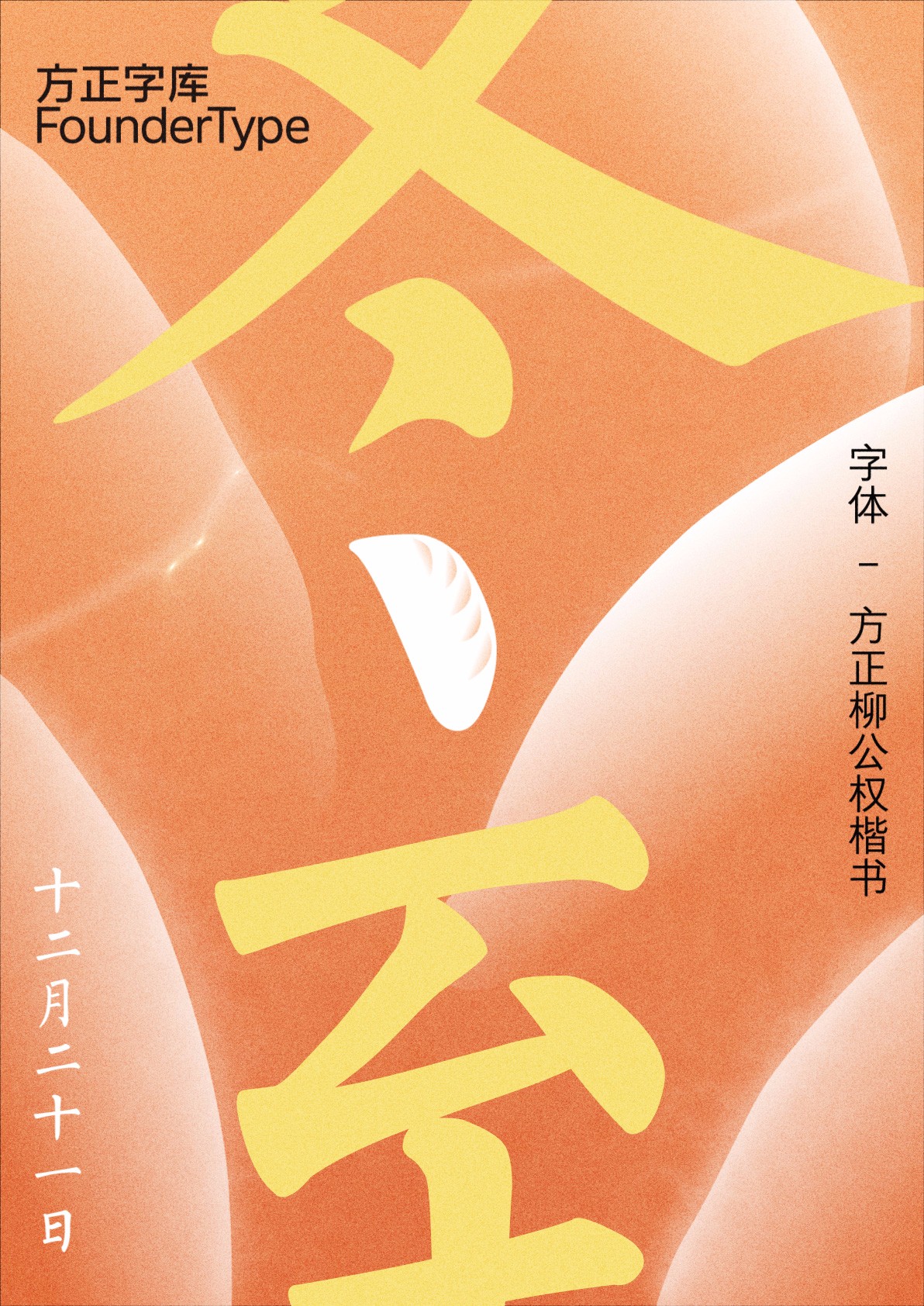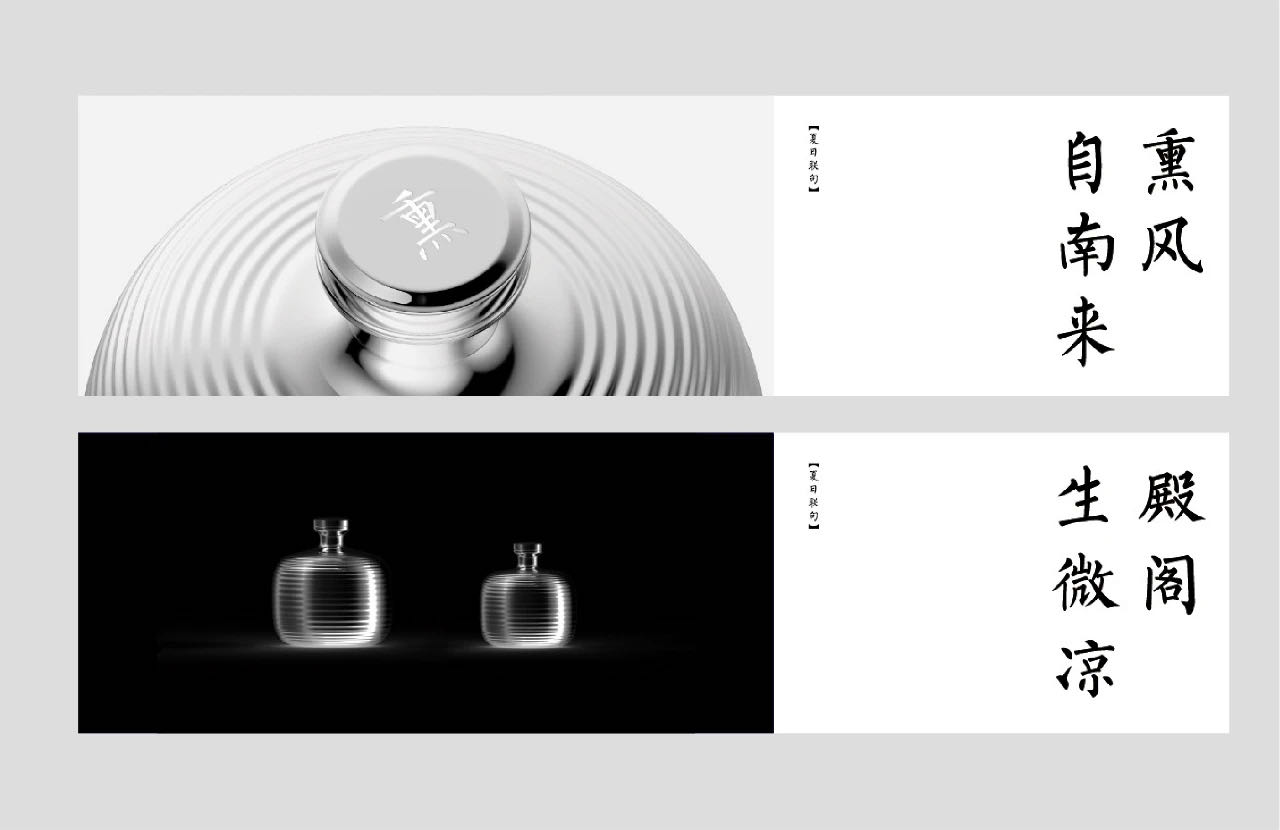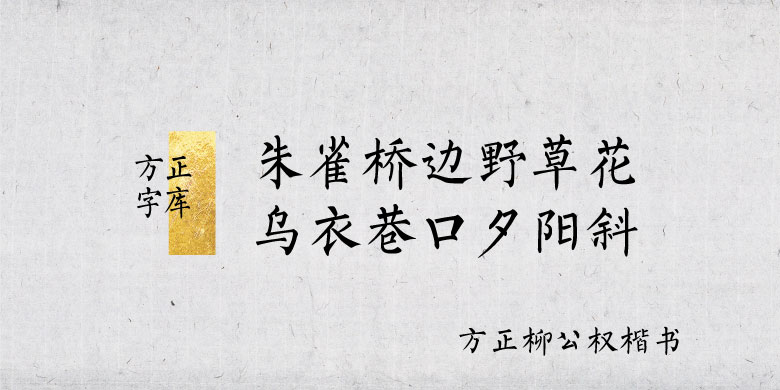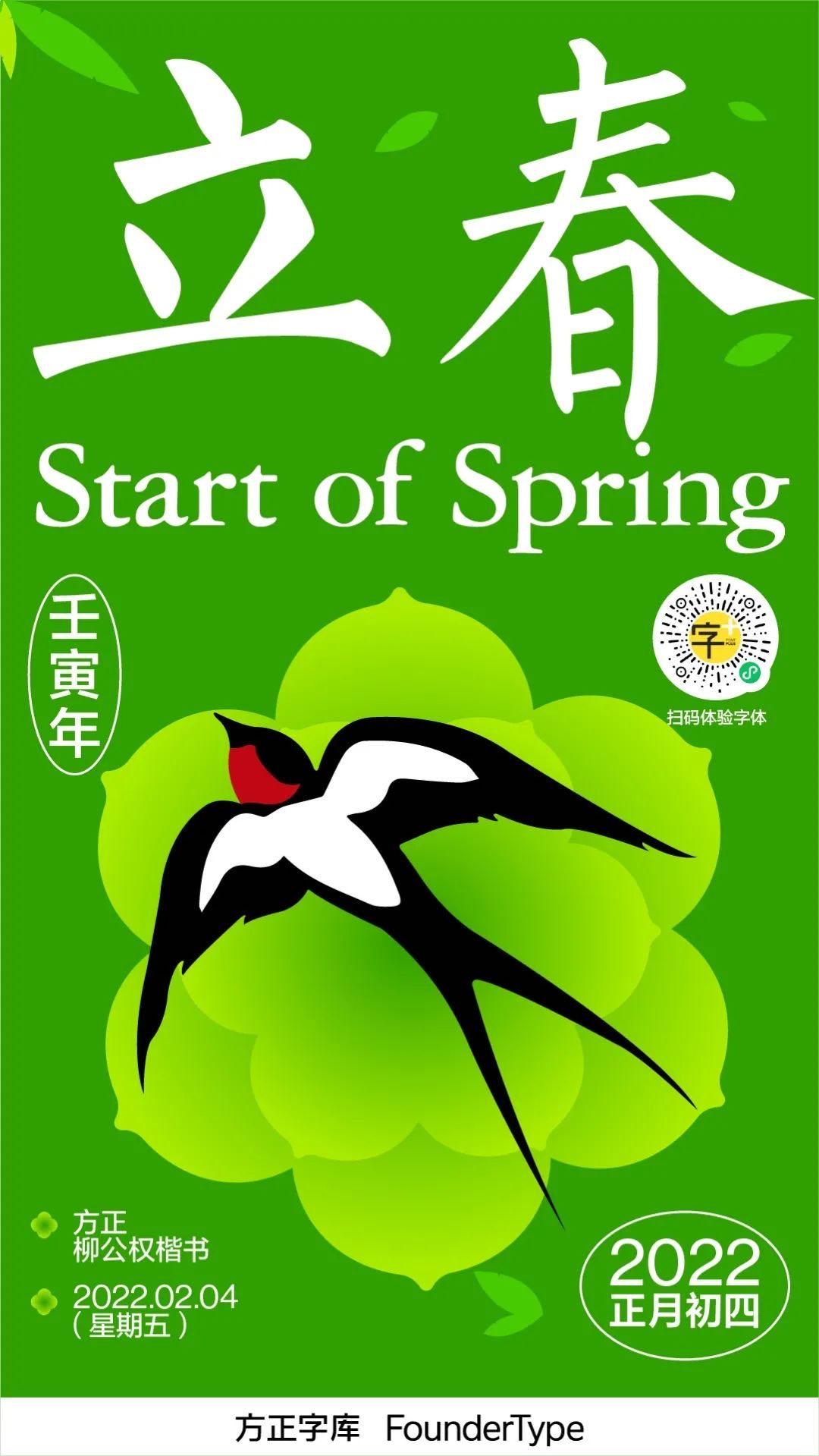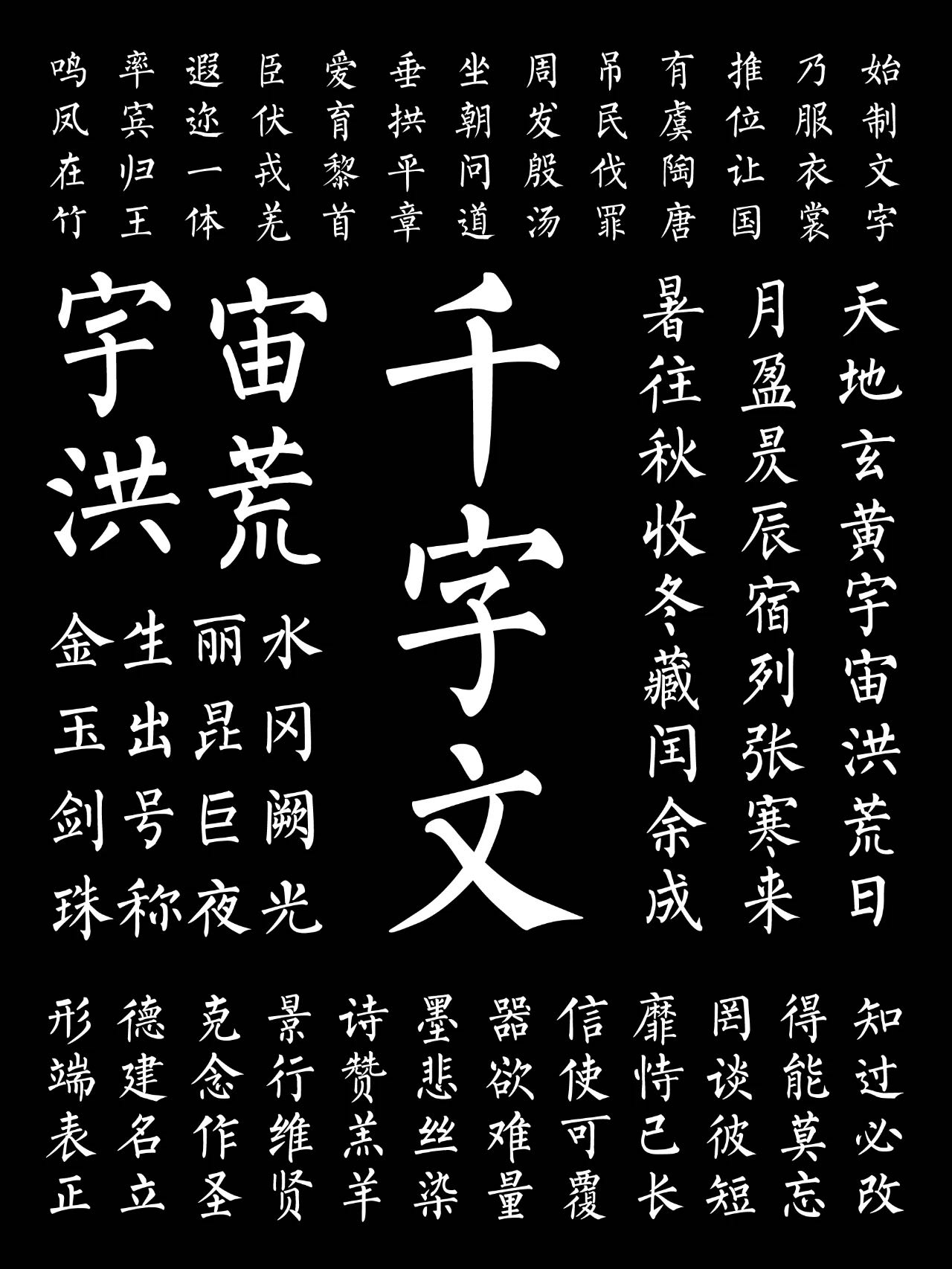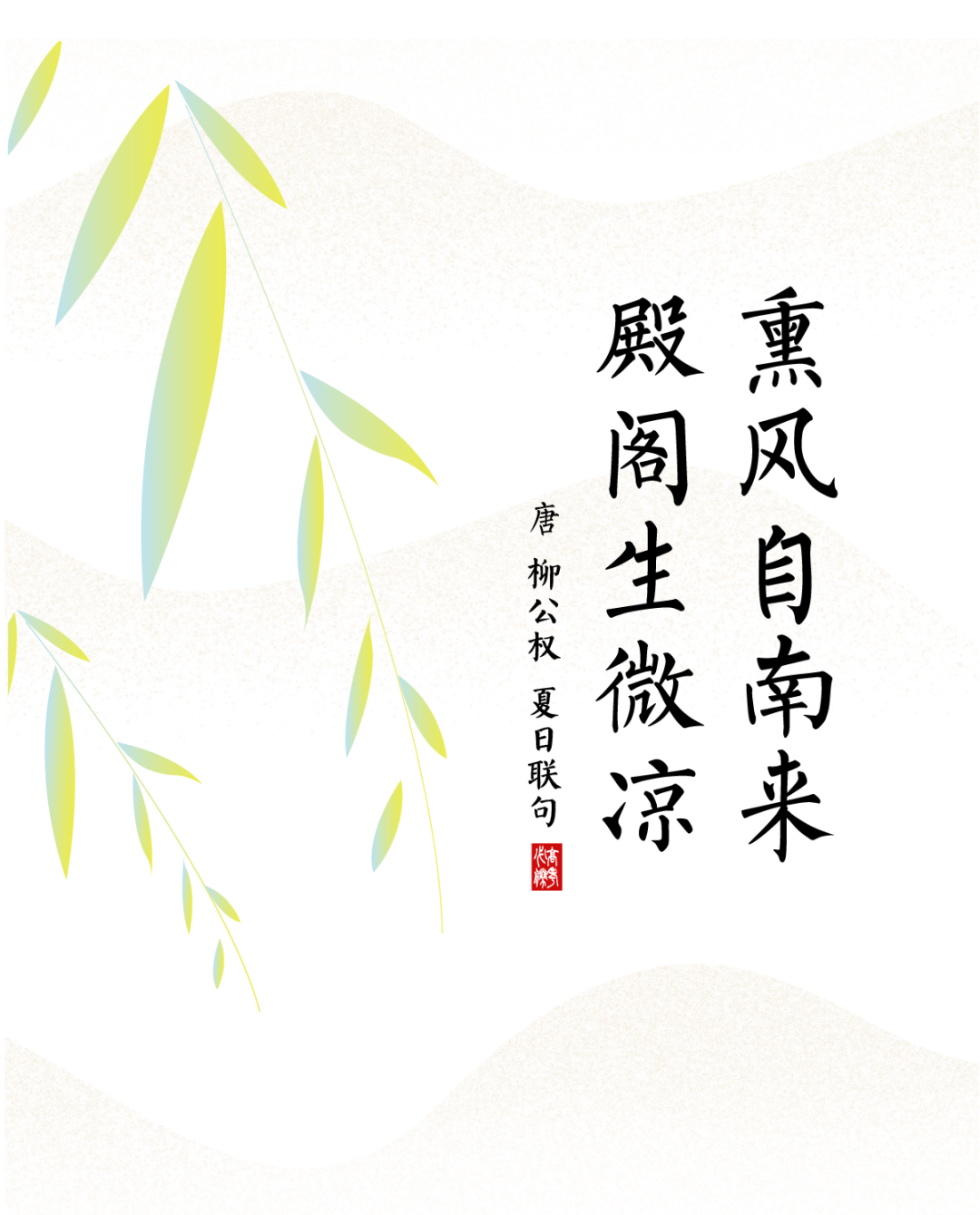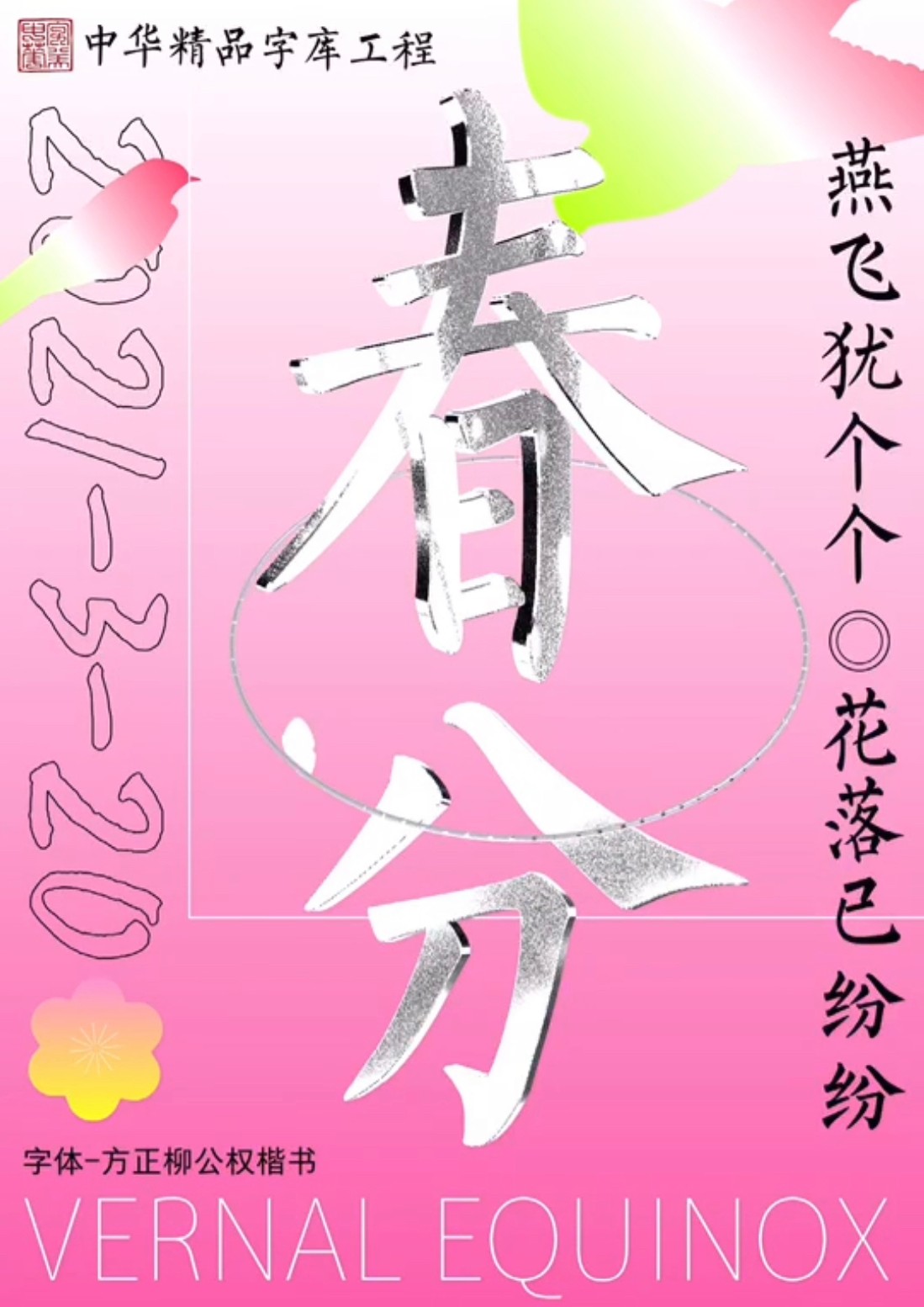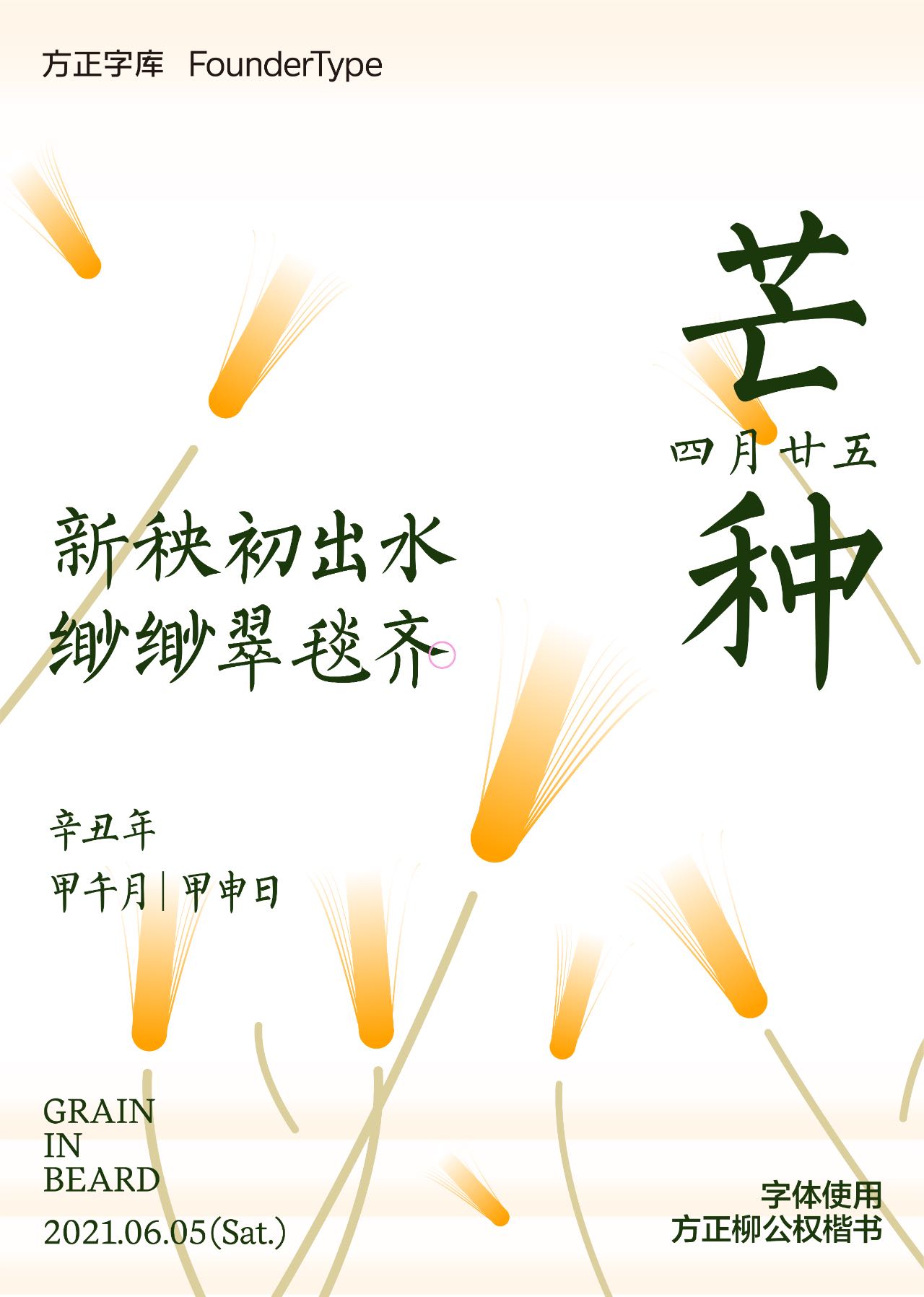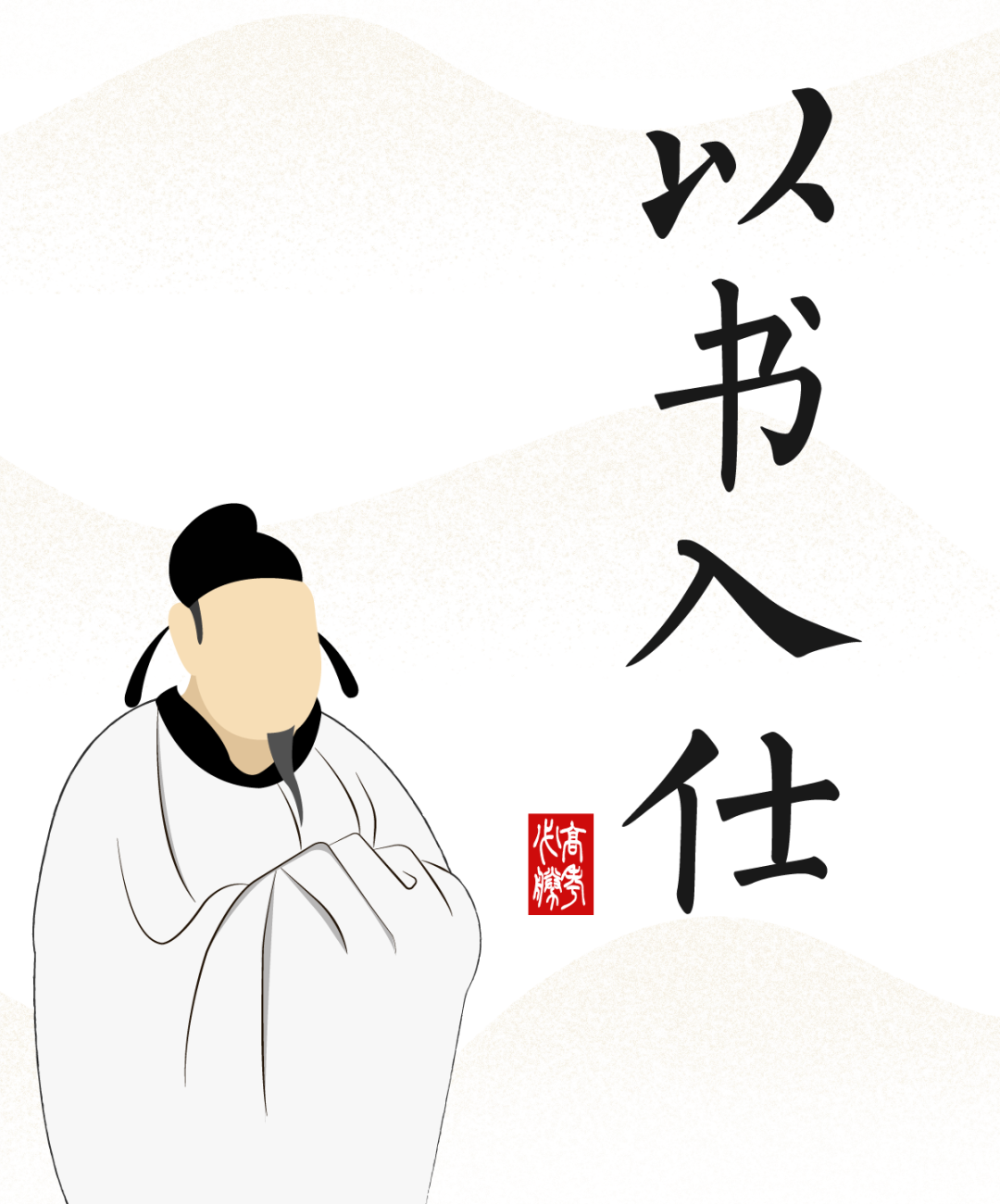
方正柳公权楷书
字体品牌: 方正字库 中华精品字库 整理/设计:苏新诗 字体分类:楷书 字体属性:精品字 字符集:简繁扩展(GBK)、大陆简体(GB2312-80) 发布时间: 2019
柳公权(778-865),唐书法家。字诚悬,京兆华原(今山西运城解州镇)人。官至太子少师。工书,正楷尤知名。初学王羲之,遍阅近代笔法,而得力于颜真卿、欧阳询,骨力遒健,结构劲紧,自成面目。对后世影响很大,与颜真卿并称“颜柳”。书碑很多,以《玄秘塔碑》、《金刚经》、《神策军碑》为最著。书迹有《送梨帖题跋》。字体特征:以《玄秘塔碑》《神策军碑》为主要开发依据。笔画遒劲、扎实、清朗, 字形工稳、挺拔、自如,体现出严谨中见疏朗的整体风姿。
柳公权与颜真卿并称“颜柳”,是“楷书四大家”之一,他一生精研书法,自成面目,留下无数传世碑刻。其高山仰止的书法地位,常常让人忽略他的另一个“学术成就”——戊子科状元。唐宪宗元和三年(公元808年),柳公权时年30岁,参加科举考试一举登进士科,而且还高中榜首,摘下状元之位。他“以书入仕”,此后一生为官,直到咸通初年以“太子太保”之职退休致仕。
柳公权书法清劲,又善诗作,深得皇帝赏识。有一次,唐文宗与诸多学士联句,文宗出上联曰:“人皆畏炎热,我爱夏日长。”当时续对的大臣很多,文宗却独独赏识柳公权的“熏风自南来,殿阁生微凉”,当下即命他将联句提于殿壁,柳公权遵旨提笔,一挥而就,其书法精妙绝伦,以至文宗赞叹:“就是钟繇、王羲之也未必能超过。”
▼方正柳公权楷书 - 排版展示及应用效果
柳公权楷书排版展示效果
柳公权楷书模拟应用效果
柳公权楷书应用 之 2020冬至海报
柳公权楷书应用 之 2021春分海报
柳公权楷书应用 之 2021芒种海报
柳公权楷书应用 之 2022立春海报